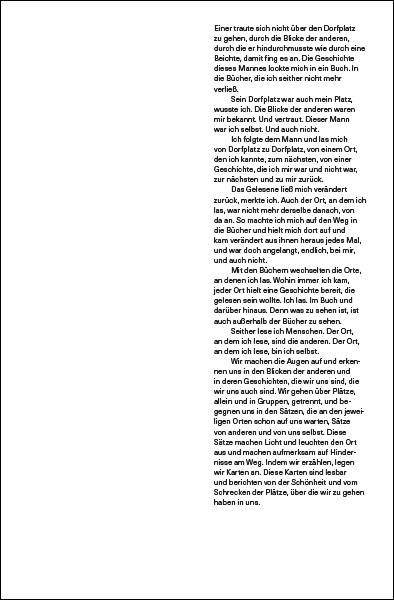
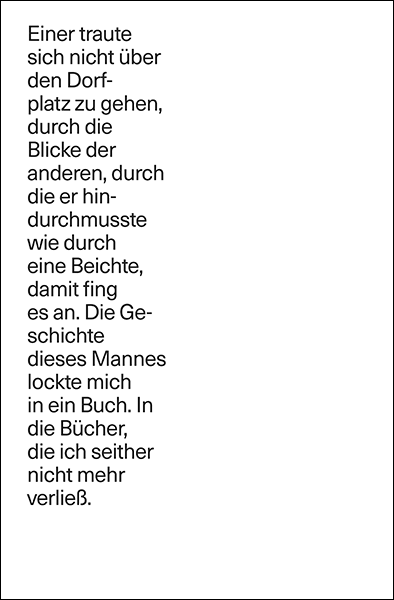
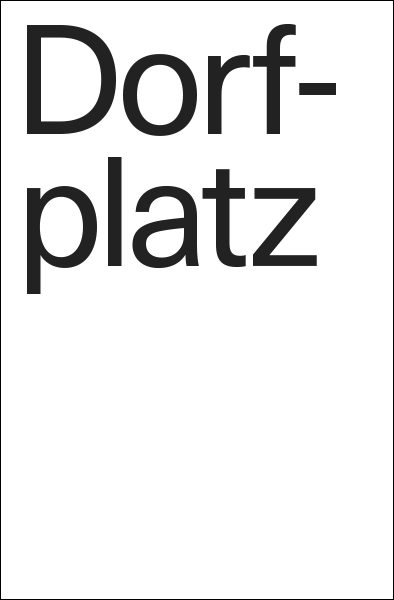
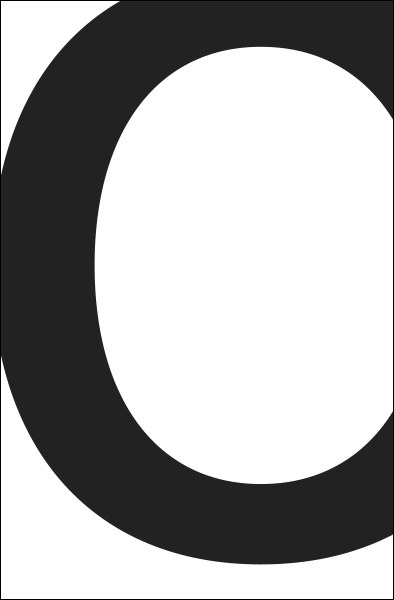
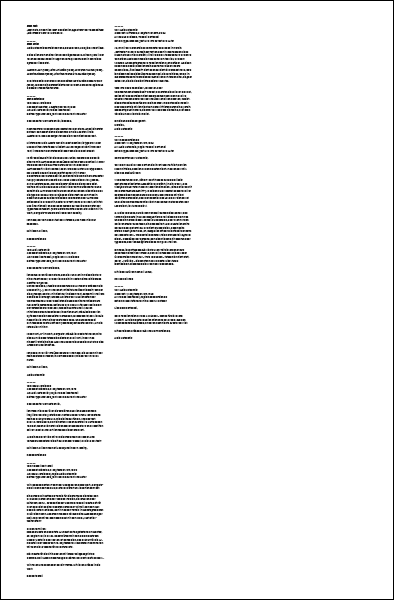
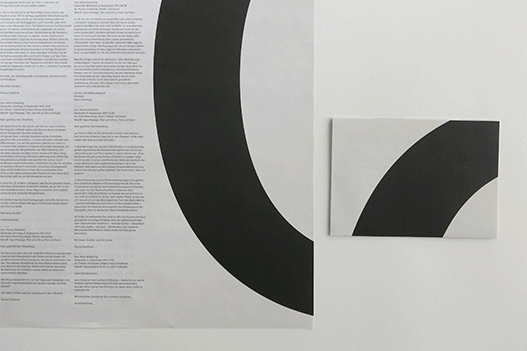
Text
Der Platz, an dem ich lese erschien im Spectrum der Tageszeitung Die Presse vom 19. März 2016.
Autor
Alois Hotschnig schreibt Romane, Erzählungen, Hörspiele und Stücke.
Seine Bücher erscheinen im Verlag Kiepenheuer & Witsch (bzw. in der Taschenbuchausgabe im Haymon Verlag und wurden in zahlreiche Sprachen übersetzt.
Auswahl: Aus (1989), Eine Art Glück (1990), Leonardos Hände (1992), Ludwigs Zimmer (2000), Die Kinder beruhigte das nicht (2006)
Zuletzt erschien der Erzählband Im Sitzen läuft es sich besser davon (2009), von dem eine dramatisierte Fassung 2016 am Schauspielhaus Salzburg uraufgeführt wurde.
Typografie und Gestaltung
Von: Paulus Dreibholz
Sehr geehrter Herr Hotschnig, liebe Eva,
nach mehreren Wochen Ruhe kommt nun der Sturm. Anbei ein erster Entwurf. Es handelt sich bei dem PDF um die 4 Poster für die Ausstellung. Das Gesamtposter habe ich noch nicht behandelt.
Hintergrund: Mein Ansatz war ein selbstreflexiver, in typografischer und schriftgestalterischer Hinsicht. Ausgangspunkt hierfür war der Text, in welchem der Protagonist auch von sich selbst erzählt.
In Kürze: Die Schrift ist die Neue Haas Unica, welche das Ergebnis einer 1977 in Auftrag gegebenen Überarbeitung von Helvetica ist. Zwar wurde der damalige Auftrag aufgrund von Insolvenz der Auftraggeberin nicht beendet, aber 2012 dann unter Monotype doch. Da Helvetica durch ihre Popularität schon mit starken Selbstreferenzen aufgeladen ist, schien mir die Wahl einer versuchten Neu(er)findung der Helvetica als Neue Haas Unica gut zu passen, zumal Letztere auch „menschlichere“ Züge als die Vorlage zeigt. Weiters wirkt die Neue Haas Unica in ihrer Form zurückhaltend und scheint die Aufmerksamkeit auf den Inhalt zu lenken. Dies wird durch die typografische Anordnung jedoch hinterfragt. Es kommt beim Sehen und Lesen zu einer ständigen Veränderung der Aufnahme zwischen Bild und Schrift, Poster und Text, Form und Inhalt, Intimität und Öffentlichkeit, und dennoch werden nur wenige Parameter der Typografie verändert. (Der zuletzt erwähnte Gegensatz schien mir im Wort „Dorfplatz“ wunderbar eingefangen zu sein.)
Ich hoffe, der Vorschlag stößt auf Interesse, und freue mich auf Feedback.
Sehr geehrter Herr Dreibholz,
ich danke Ihnen für den Sturm, den Sie nun auch in meine Richtung hin entfacht haben, und den ich als ein im besten Sinne reinigendes Gewitter empfinde.
Um genau diese „ständige Veränderung der Aufnahme zwischen Bild und Schrift, (…), Form und Inhalt, Intimität und Öffentlichkeit“, von der Sie sprechen, geht es mir nicht nur in diesem Text, sondern in meinem Schreiben überhaupt, um das Anbieten von Möglichkeiten der Wahrnehmung und der dabei ständig und eben immer wieder aufs Neue nötig werdenden Justierung und Nach-Justierung und in allem der Vergewisserung dessen, was sein könnte und ist, durch Irritationen erzähl-technischer, inhaltlicher Art, wie Sie sie eben im optischen Bereich anzubieten versuchen, vorausgesetzt, dass ich Sie hoffentlich in Ihrem Sinne verstanden habe. Und um den dabei entstehenden Kontakt mit dem (lesenden) Betrachter geht es, um die Interaktion mit ihm.
In dem Ort „O“ im Wort „Dorfplatz“, wie Sie ihn gestaltet haben, wird diese Ambivalenz tatsächlich sichtbar, als ein Ort, in den man hinabstürzt wie in einen Abgrund und der sich zugleich auftut als eine Arena der Möglichkeiten.
Ich danke Ihnen für Ihre Überlegungen und hoffe, Sie können mit den meinen etwas anfangen, in Vorfreude darauf, wieder von Ihnen zu hören.
Sehr geehrter Herr Hotschnig,
ich freue mich sehr über die verblüffend ähnliche und dennoch inspirierende Interpretation des Textes und der Grafik. Ich verstehe meinen Entwurf genau so, wie Sie ihn ausführen, und den Text ebenso. Verblüffend, da mein Entwurf doch zuerst eine Härte an den Tag legt, welche sich erst bei genauerer Beobachtung und Investition seiner selbst als wesentlich menschlicher offenbart.
Allerdings drängt sich mir nun die Frage nach Verbesser- und Veränderungsnotwendigkeit auf: genauer gesagt, ob diese besteht?
Wir finden den Entwurf sehr klar und spannend! Das Wort „Dorfplatz“ groß in den Raum des MQ zu stellen gefällt uns inhaltlich sehr gut.